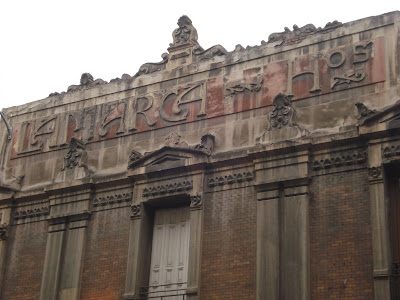
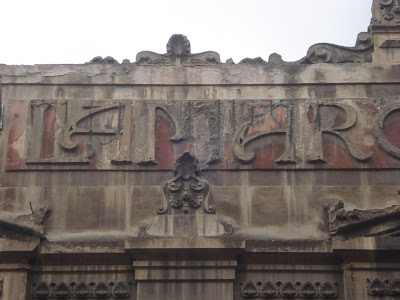
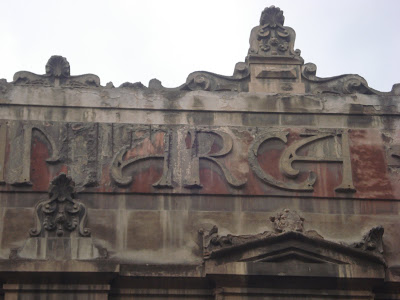
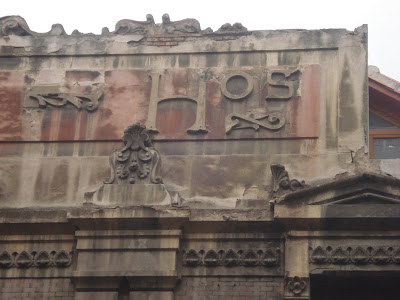
En la calle Fernando VI, números 10 y 12.
El rótulo corona el frontón que centra el antiguo edificio industrial construido en 1902 por el arquitecto Santiago Castellanos para la sociedad Lamarca Hermanos.
Su estado ruinoso apenas permite apreciar uno de los ejemplos más destacados en Madrid de tipografía modernista o Art Nouveau, caracterizada por sus formas sinuosas y su fantasía.